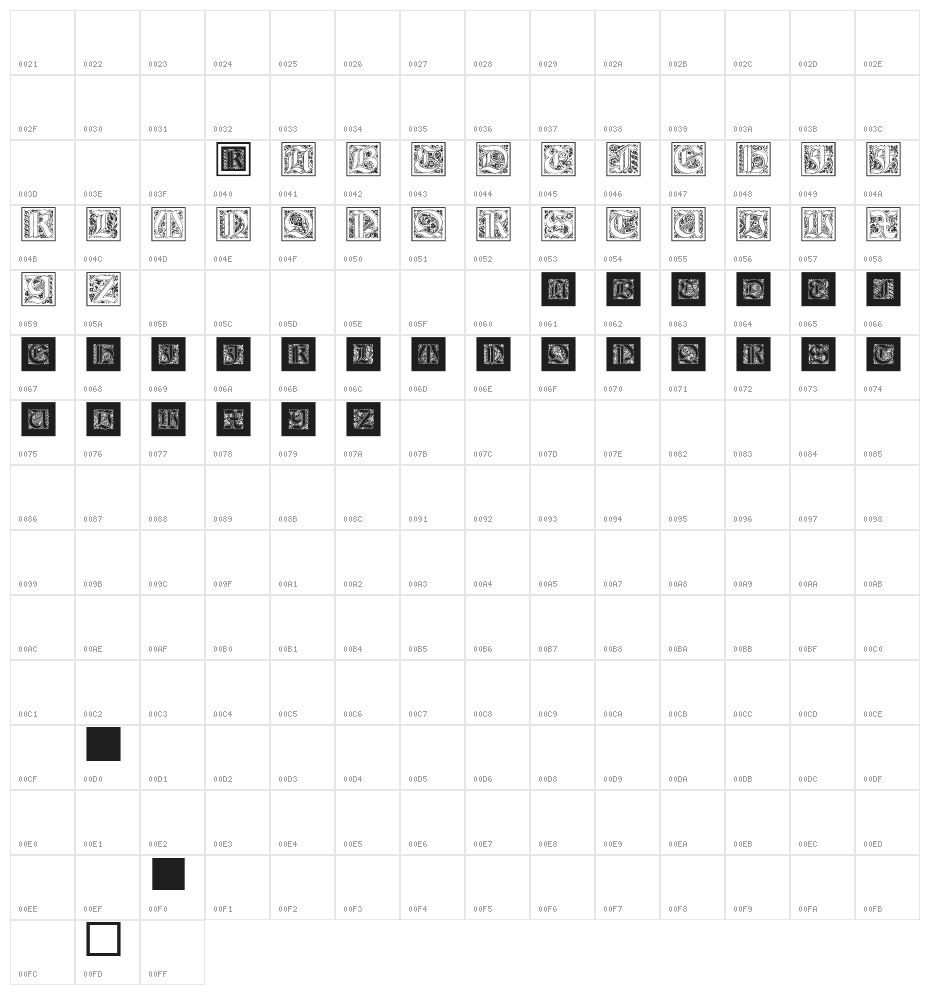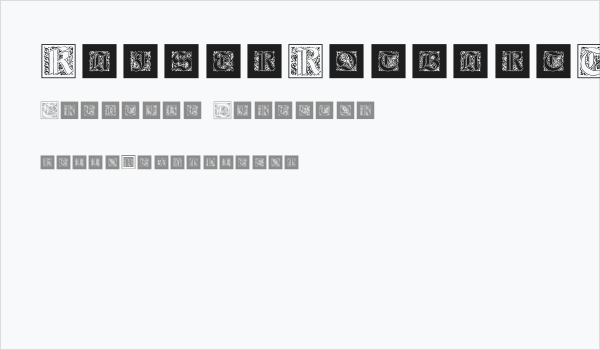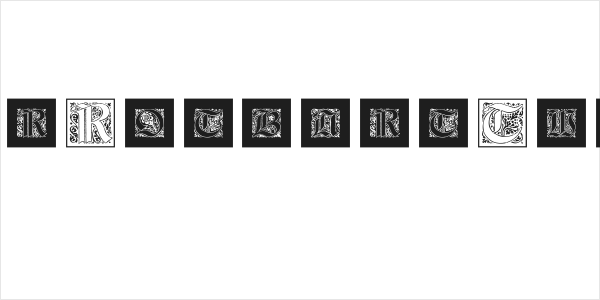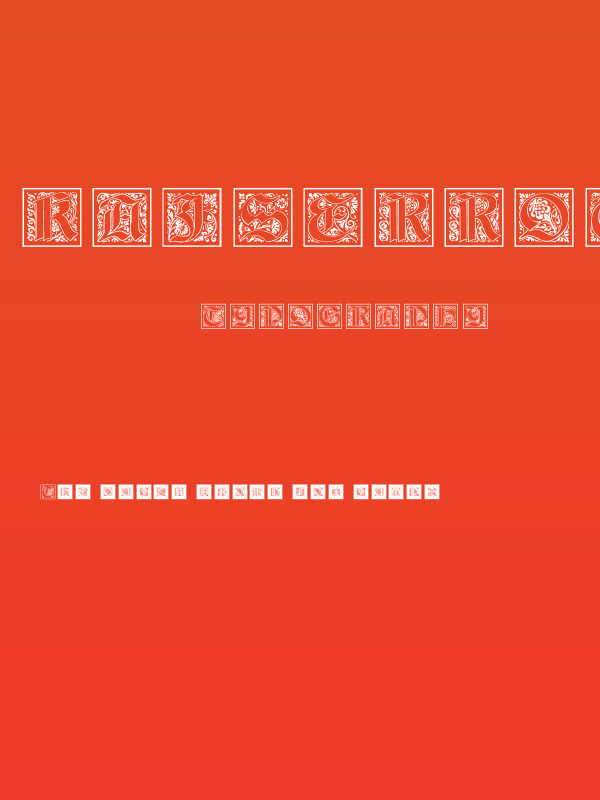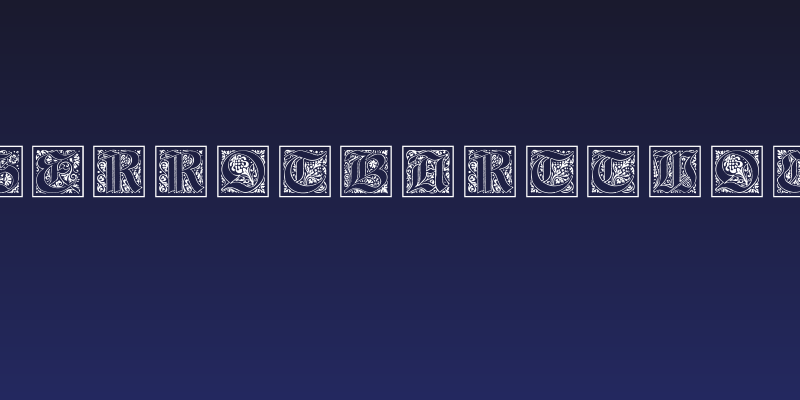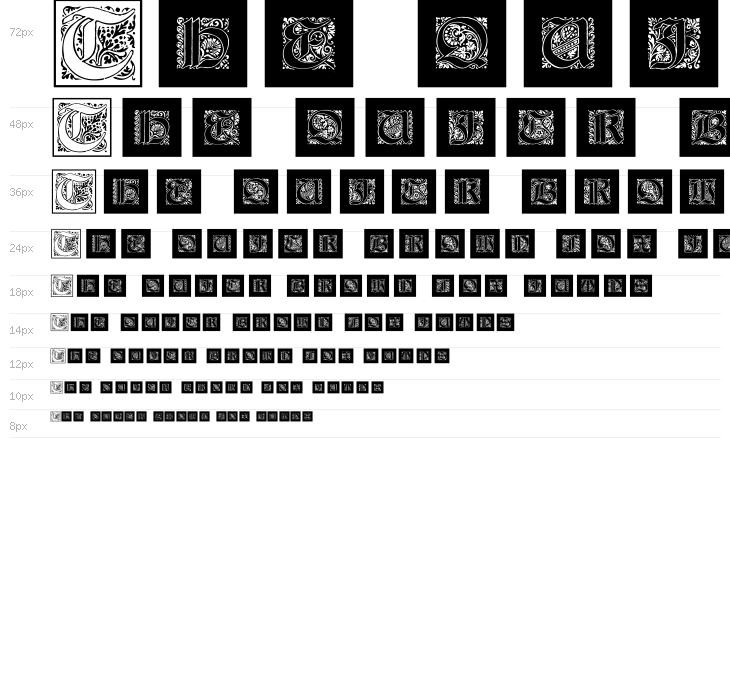
KaiserRotbartTwoCaps Font
✎ Retro
| Caz de utilizare | Logos, Headlines, Decorative elements |
| Proiecte propuse | Ideal for use in historical-themed projects, invitations, book covers, or any design requiring a touch of elegance and sophistication. |